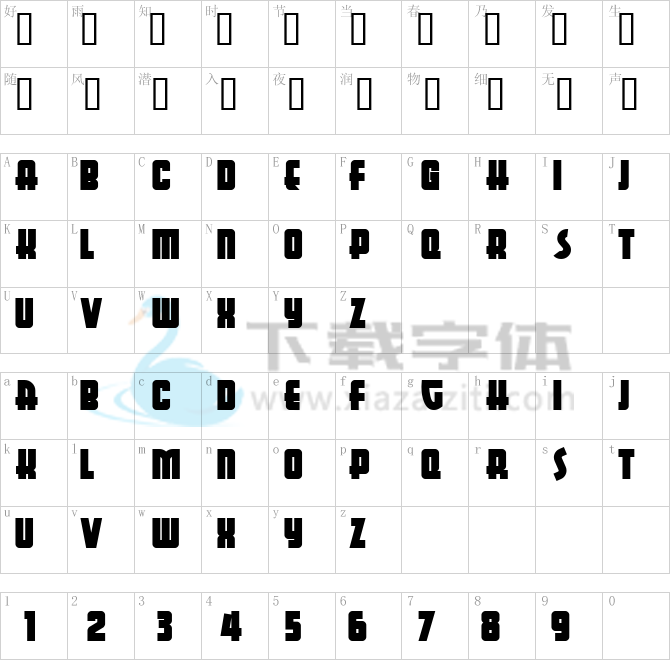
AerojonesNF.ttf字体下载,这款字体结构工整、笔画清晰,兼顾美观与易读性,适用于标题、正文、海报、包装、LOGO 等多种场景。字形优雅稳定,风格百搭耐看,适配日常排版与创意设计,让文字呈现更舒适、更具质感。AerojonesNF.ttf字体下载一笔一画,皆是细节,以均衡的比例、流畅的线条打造舒适视觉体验,字形端正大气,风格简约现代。无论是商业设计、品牌宣传还是日常排版,都能轻松驾驭,让文字更有格调与力量。AerojonesNF.ttf字体下载字体下载。